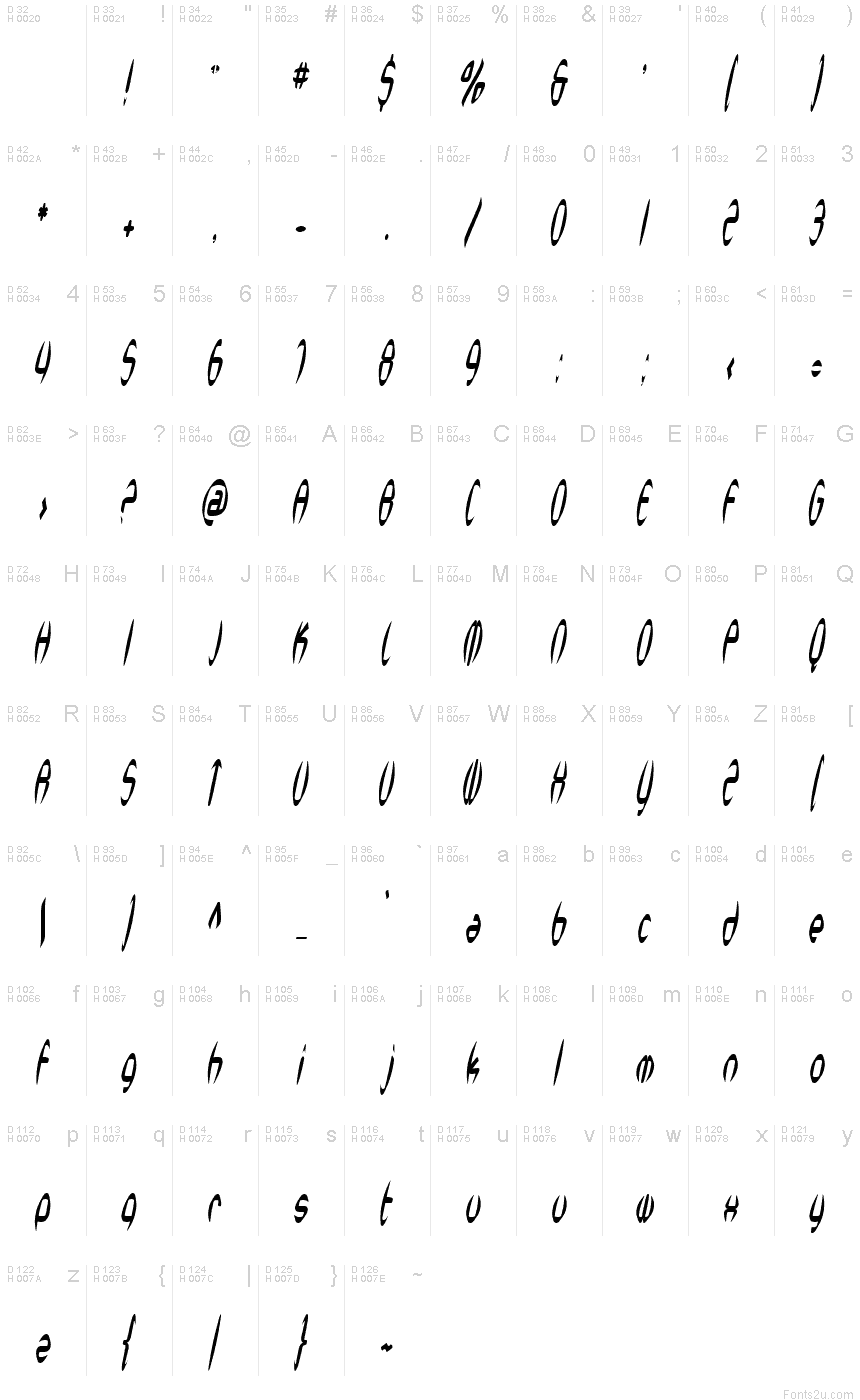
SF Synthonic Pop Condensed Oblique von ShyFonts Type Foundry ist eine kostenlose, verzerrte Comic-Display-Schrift mit einem geschmeidigen Synth-Pop-Vibe. Die Buchstaben sind stark geneigt und dehnen sich in spitze, wellenförmige Kurven aus, was dem Alphabet eine gummiartige Retro-Futurismus-Dynamik verleiht, die eher an Pop-Grafik als an klassische Comic-Schriften erinnert.
Verwenden Sie diese kostenlose Schrift, wenn Ihre Überschrift Bewegung braucht: Musikposter, Club-Flyer, Arcade-inspiriertes Branding, Magazin-Cover und Titelkarten passen perfekt zu ihrem schwungvollen Rhythmus. Sie eignet sich auch hervorragend für kurze Logos oder große, prägnante Wörter, da die langen, sich verjüngenden Formen selbst kurzen Zeilen Lebendigkeit verleihen.